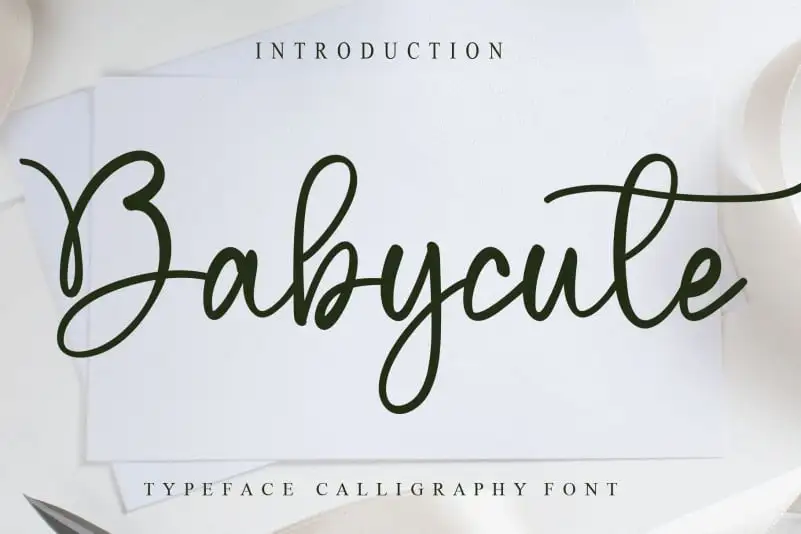
A ‘Babycute Script Font’ é uma deliciosa adição ao seu arquivo de fontes, projetada especialmente para artistas e designers que buscam uma letra delicada e encantadora para seus trabalhos. Desenvolvida pelo designer criativo da CreativeLetter, essa fonte traz um toque especial à sua produção, com linhas fluidas e traços leves, perfeitas para criar mensagens suaves e emotivas. Com a ‘Babycute Script Font’, você pode explorar seu talento em uma nova dimensão, criando headlines encantadores ou textos de forma elegante que chamem a atenção de qualquer público. Essa fonte oferece um toque infantil ao mesmo tempo que mantém um grau de sofisticação, tornando-a perfeita para aplicar em rótulos de produtos infantis, camisas com mensagens personalizadas ou até mesmo em texturas de design gráfico delicado. Seja você designer de arte digital, ilustrador ou simplesmente alguém que gosta de adicionar um toque especial aos seus projetos, a ‘Babycute Script Font’ não poderia ser mais perfeita para o seu projeto.